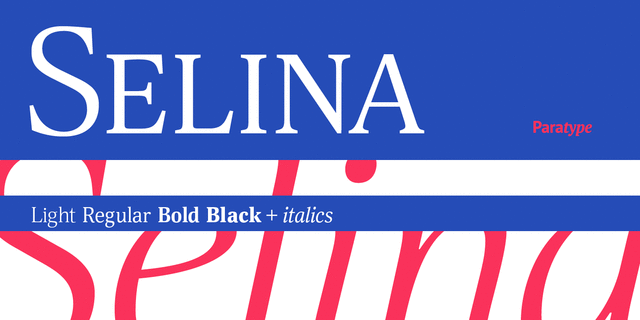
Шрифт разработан для компании ПараТайп дизайнером Натальей Васильевой в 2007 году. Текстовая гарнитура из 8 начертаний универсального назначения. Кроме того, к ней разработан декоративный каллиграфический курсив, включающий прописные буквы с росчерками. Отличается малой контрастностью и несколько зауженными пропорциями. Экономична и хорошо читается в мелких кеглях. Для текстового и акцидентного набора. В 2010 году выпущена переработанная версия с расширенным комплектом знаков.
Ассоциации c семейством SelinaКачества и характер:
спокойный, гармоничный, тонкий, легкий, понятный, средний, уравновешенный, умеренный, техничный, современный, неброский, культурный, образованный, устойчивый, гуманитарный, вежливый, убедительный, авторитетный, мотивирующий, ответственный, старинный, исторический, свадебный, сказочный, мастерский, художественный, благородный, ювелирный, утонченный, красивый, выразительный, характерный, прекрасный, ажурный, праздничный, музыкальный, романтичный, творческий